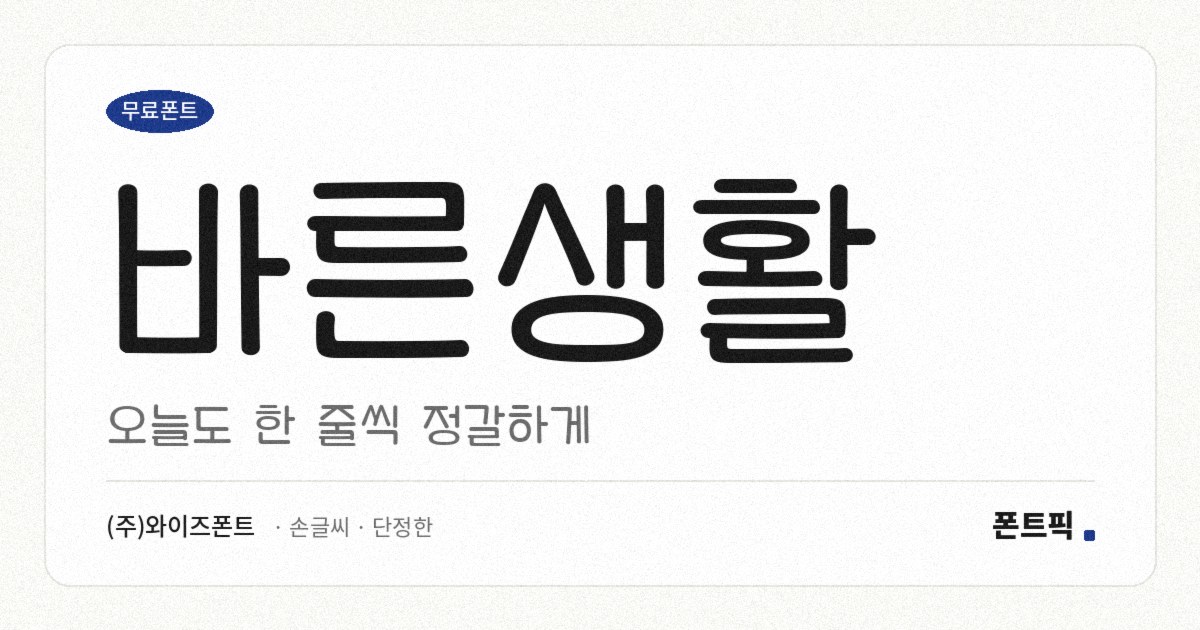
바른생활
TDTDRightLife
이름 그대로 단정한 서체입니다. 획이 고르고 장식이 없으며, 글자와 글자 사이가 눈에 띄게 넓습니다.
파일에서 재어 보면 받침 유무에 따른 높이 차가 거의 없는 네모틀이고 낱자는 정사각형에 가까우며, 가로세로 획의 굵기 차이도 크지 않습니다. 여기에 넓은 자간이 더해져 글자 하나하나가 또렷하게 떨어져 보입니다. 글자를 익히는 사람이 형태를 구분하기 쉽도록 만든 서체의 성질입니다.
받아쓰기 학습지나 어린이 교재, 안내문처럼 글자가 또렷하게 읽혀야 하는 자리에 맞습니다. 반대로 자간이 넓어 같은 분량이라도 자리를 많이 차지하니 공간이 빠듯한 조판에는 불리합니다. 현대 한글 11,172자를 모두 담았고 굵기는 하나입니다.